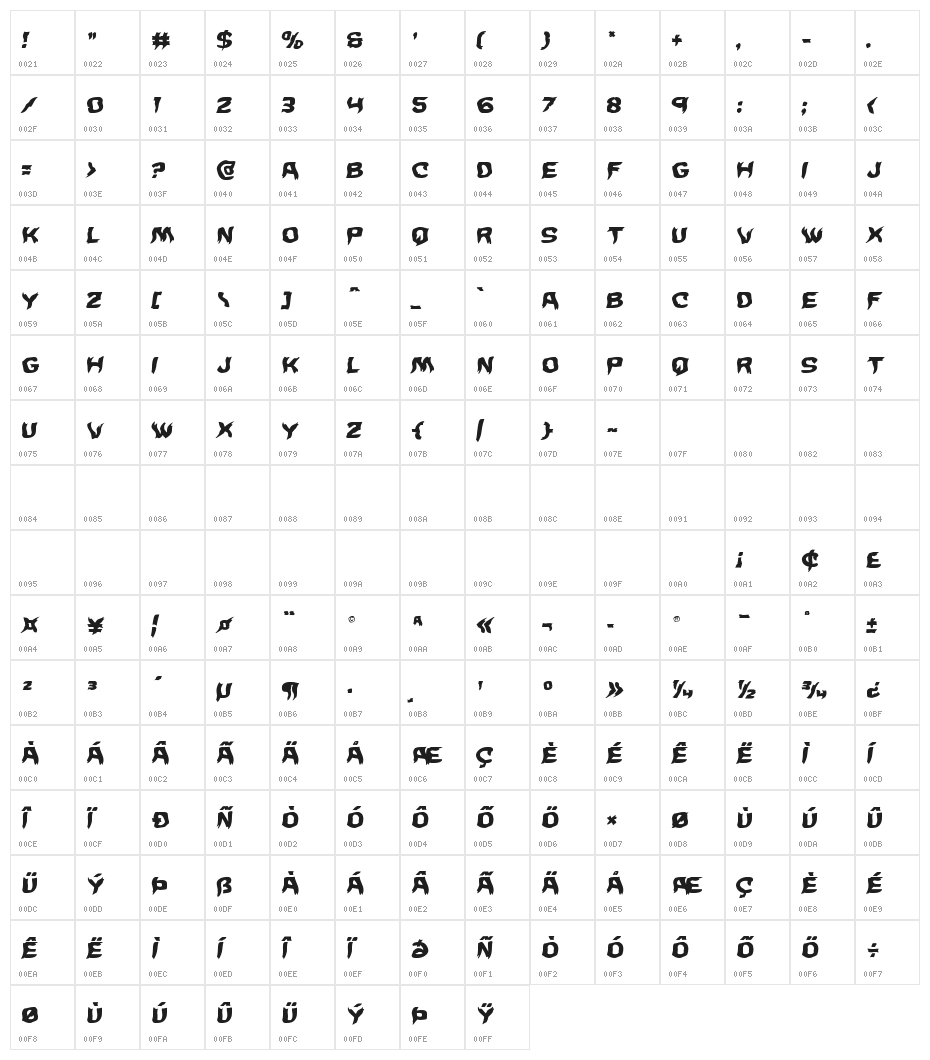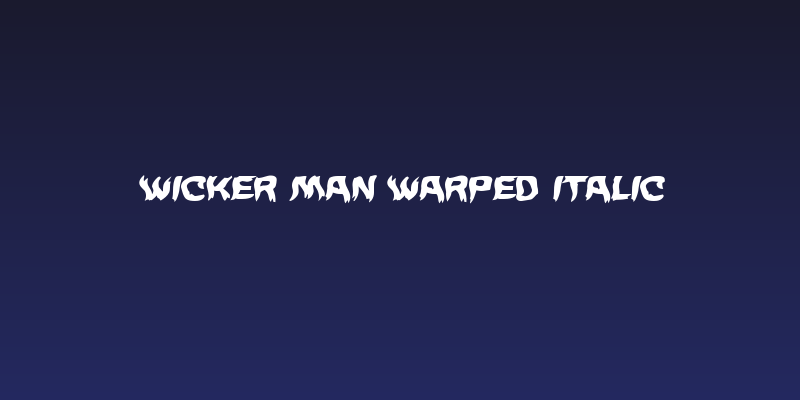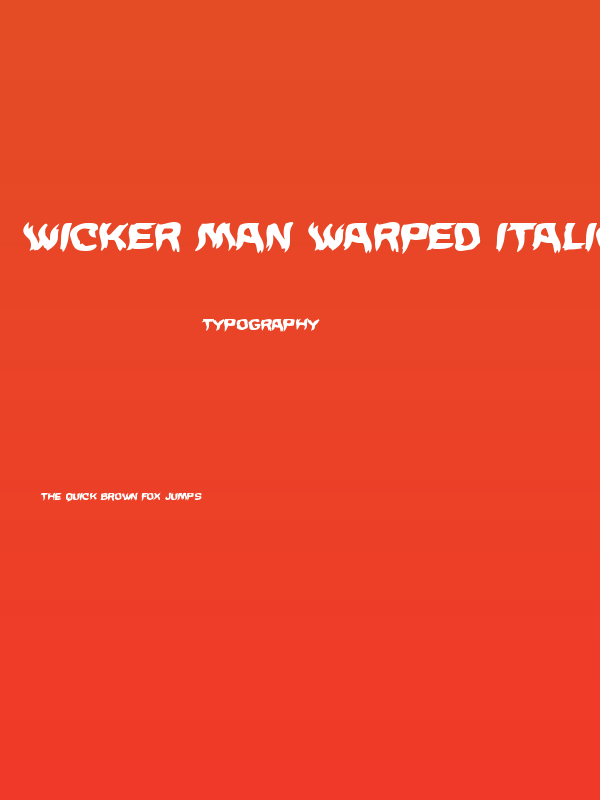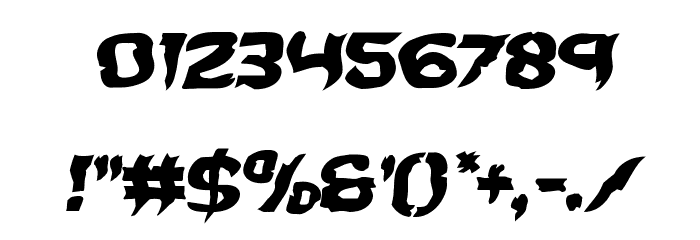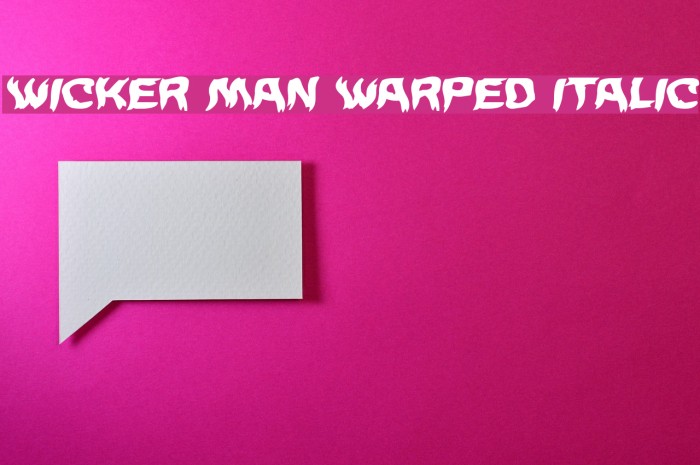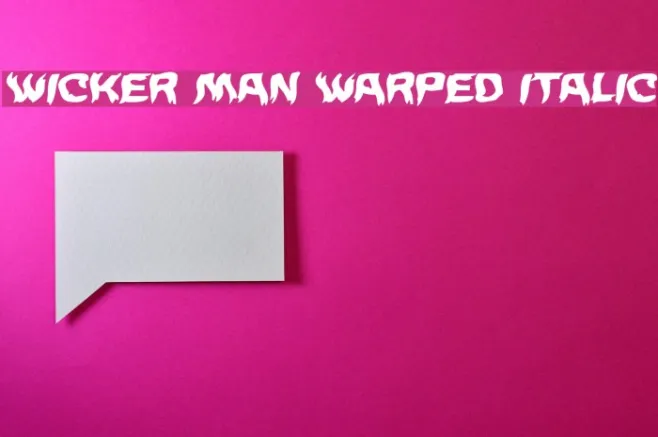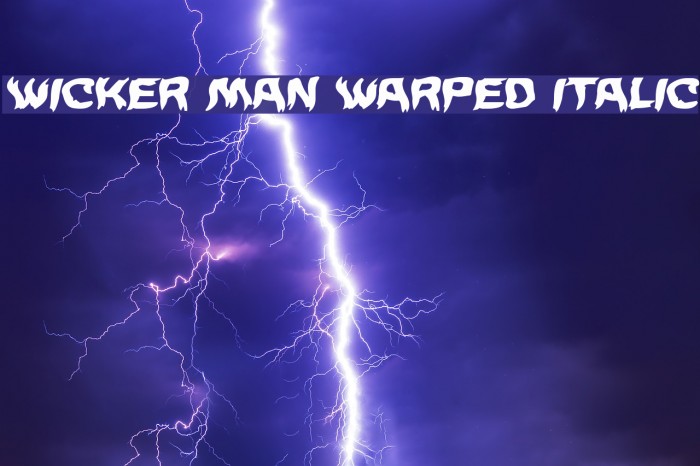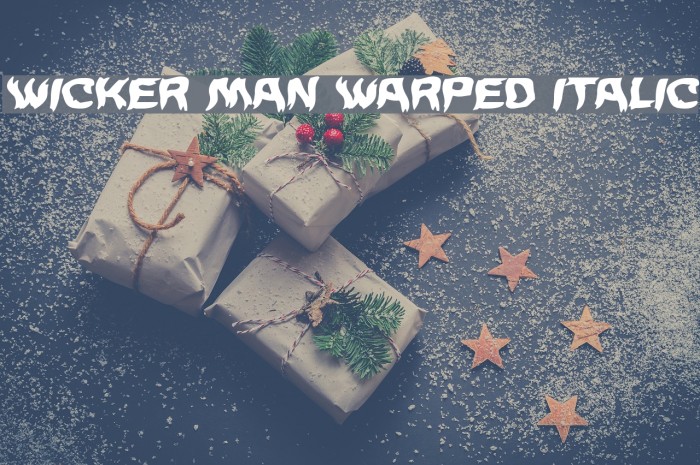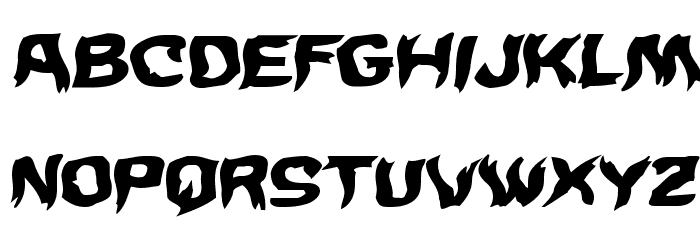
Wicker Man Warped Italic Font
✎ Distorted Eroded
| Vorgeschlagene Projekte | Perfect for horror-themed posters, edgy branding, album covers, and Halloween event promotions. |